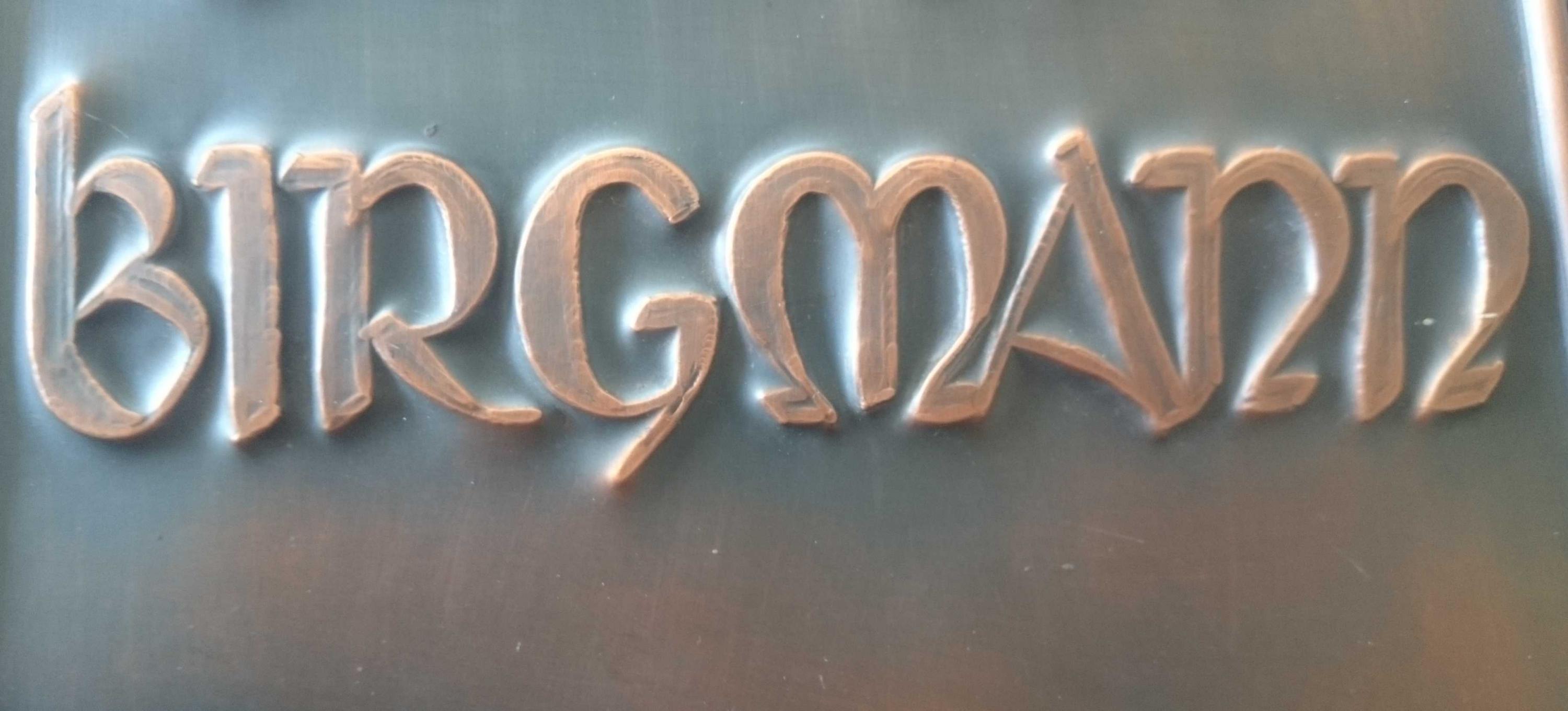
Ich weiß, es ist eine Handgeschriebene (besser gesagt in Kupfer getriebene) Schrift von meinem Vater. Er hat sie damals (90er Jahre) aus einem Buch abgezeichnet... soviel war noch herauszufinden. Nur ist das Buch leider spurlos verschwunden und im Netz bin ich einfach nicht fündig geworden. Von den 'N' kommt die Schrift 'Tintoretto' vielleicht noch am nächsten, doch der ganze Rest passt so gar nicht.
… oder "Unziale", "Uncial", beispielsweise findest du hier viele formal ähnliche: